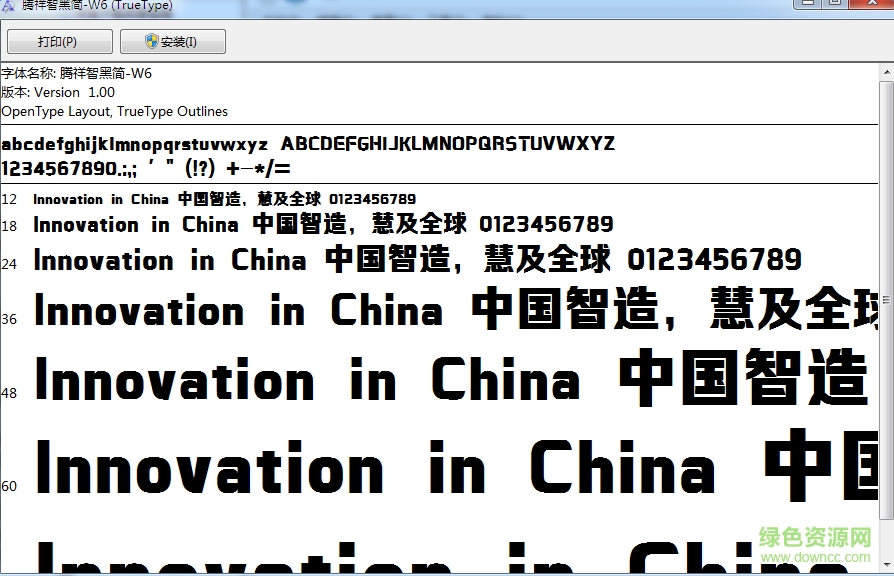
騰祥智黑簡(jiǎn) w6
騰祥智黑簡(jiǎn)w6是一款超粗的黑體字體,字體端正,大氣、壁畫(huà)橫平豎直,筆跡全部一樣粗細(xì),整體效果十分不錯(cuò),可適用于廣告設(shè)計(jì)、平面設(shè)計(jì)、印刷包裝、報(bào)紙雜志等行業(yè),有需要就來(lái)綠色資源網(wǎng)下載吧!
騰祥智黑w6是騰祥公司自主精心設(shè)計(jì)開(kāi)發(fā)的黑體系列字庫(kù)。騰祥智黑是騰祥睿黑的兄弟篇,風(fēng)格相近但排版效果迥異,不管是常用字或是非常用字,字字精美、結(jié)構(gòu)端正、重心平穩(wěn)、美觀實(shí)用。W6為超粗黑一款粗壯、醒目適用于標(biāo)題、大標(biāo)題、海報(bào)及大型廣告招貼戶(hù)外廣告等。
騰祥智黑簡(jiǎn)w6